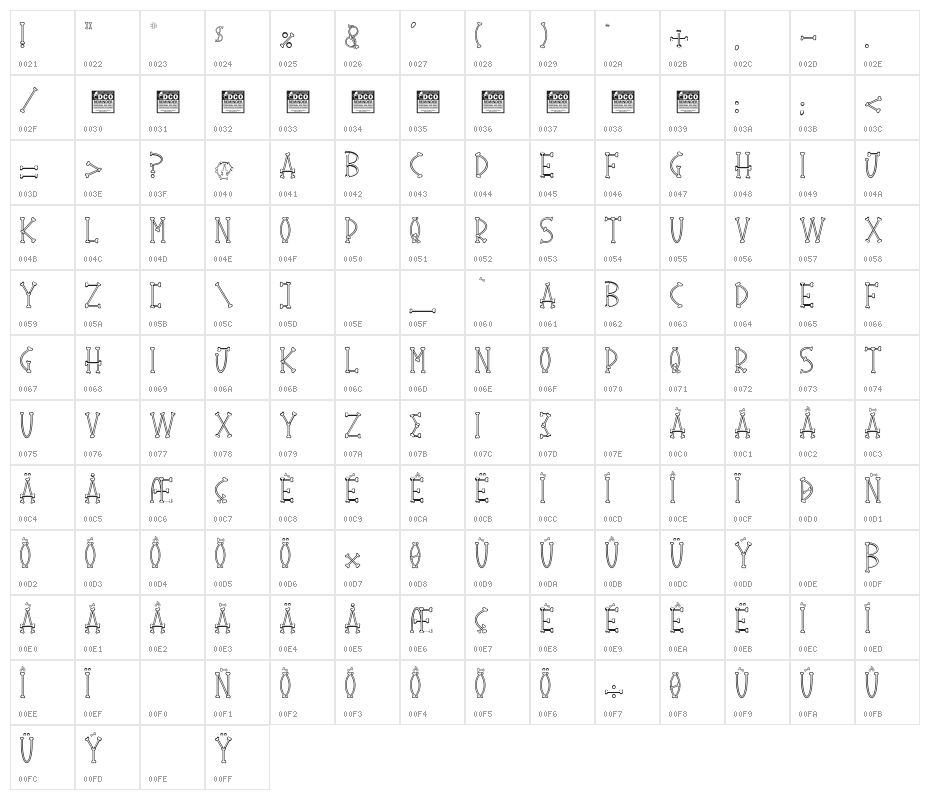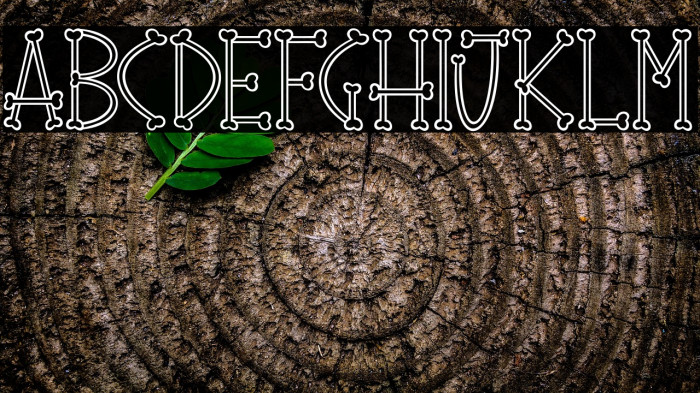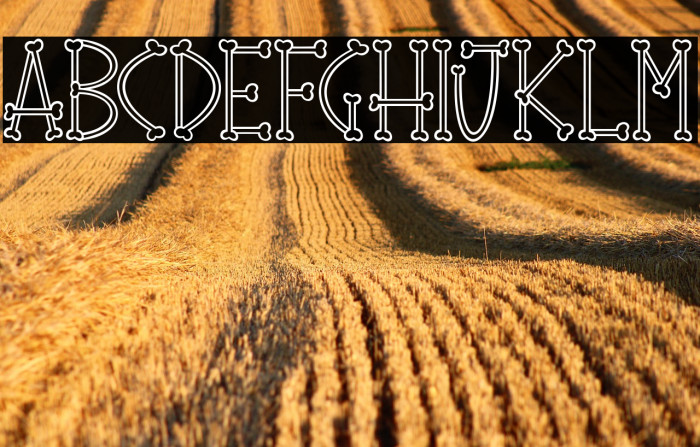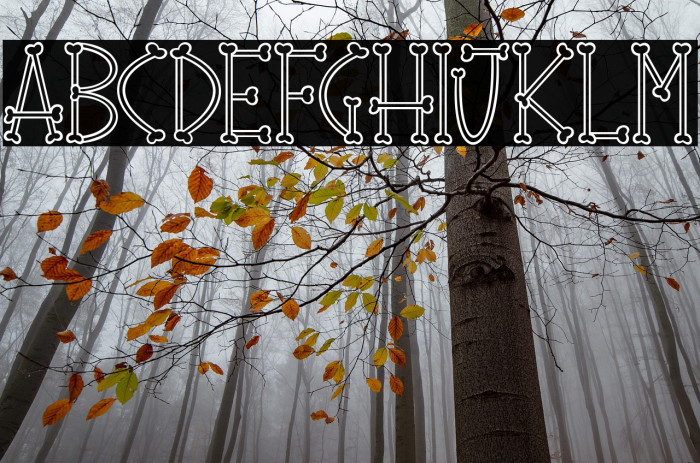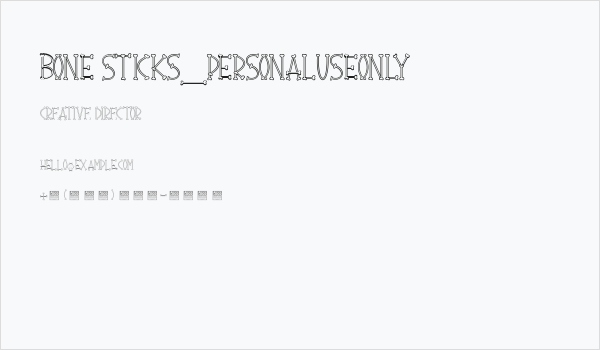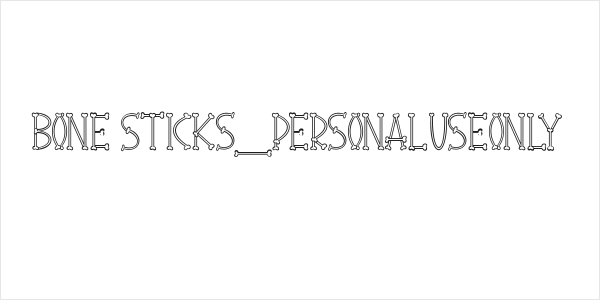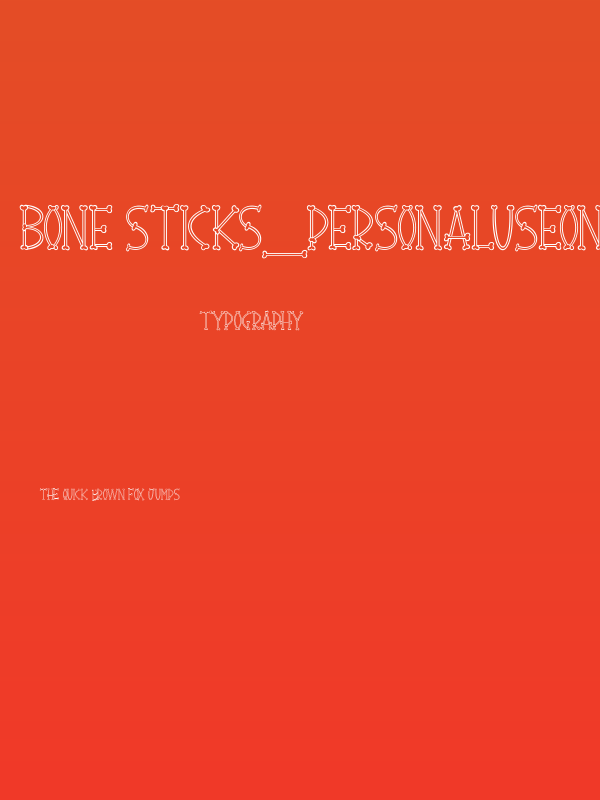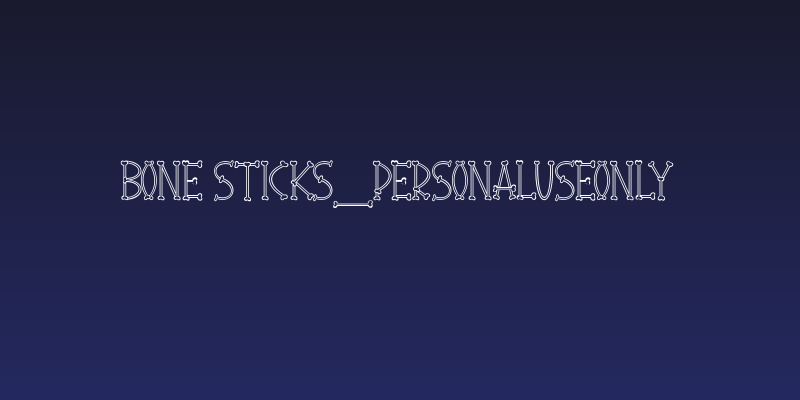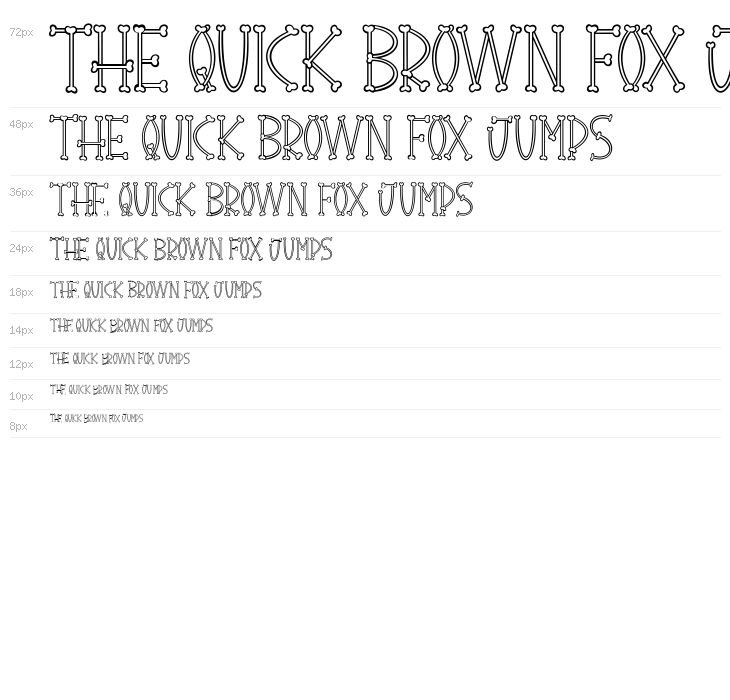
Bone Sticks_PersonalUseOnly Font
| 使用场景 | Headlines, Logos, Themed Events |
| 推荐项目 | Ideal for Halloween invitations, themed party decorations, children's book titles, or any project needing a quirky, eerie touch. |